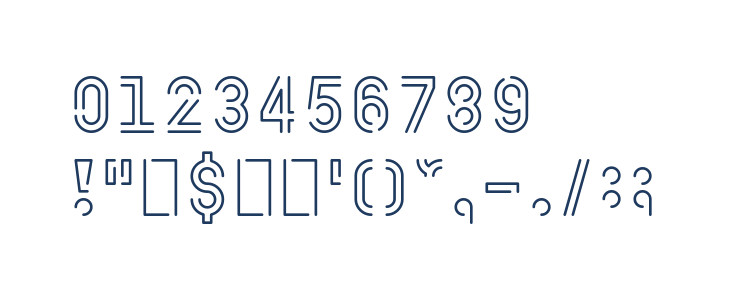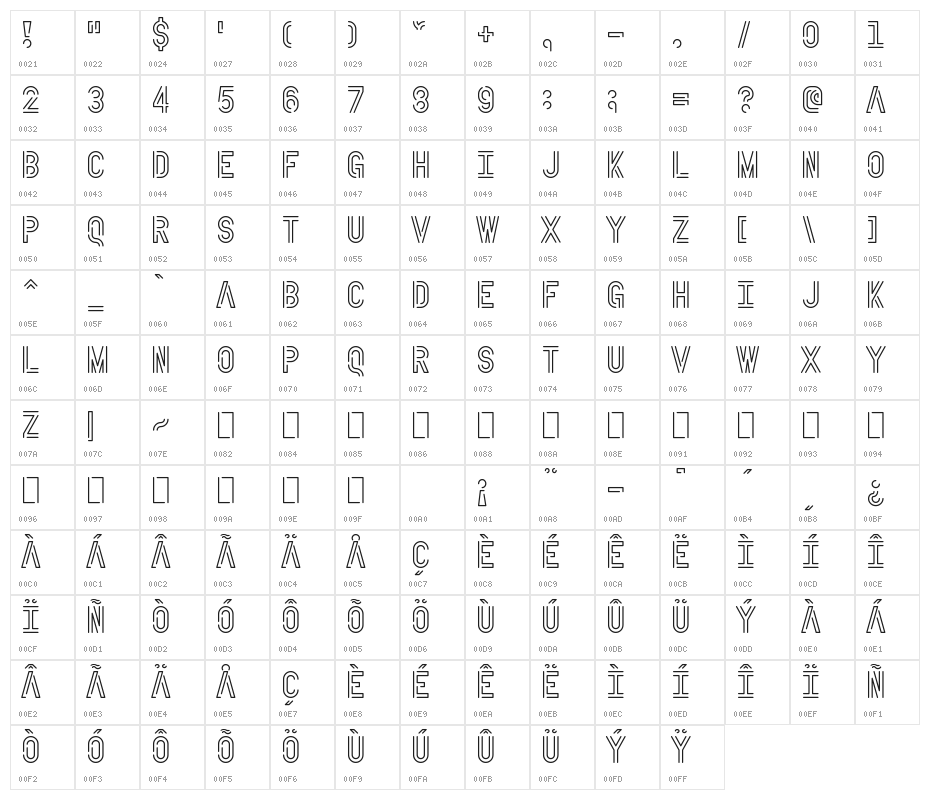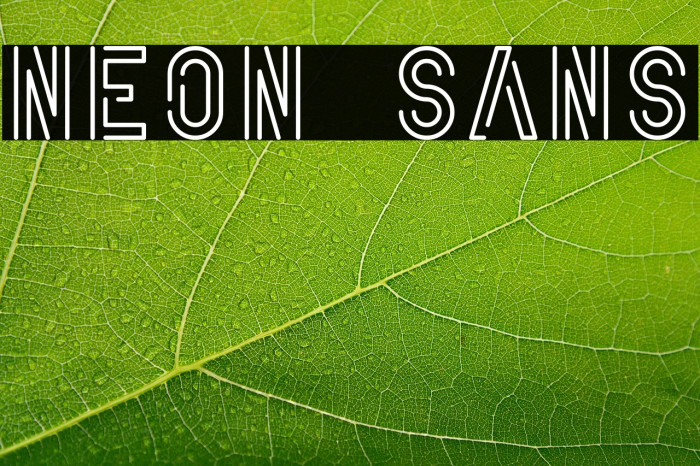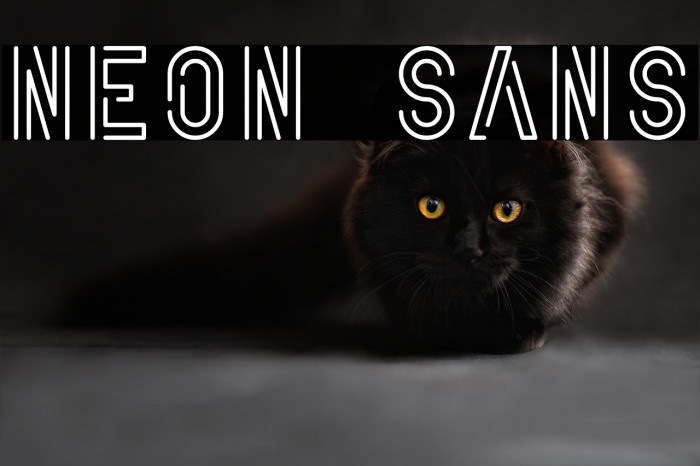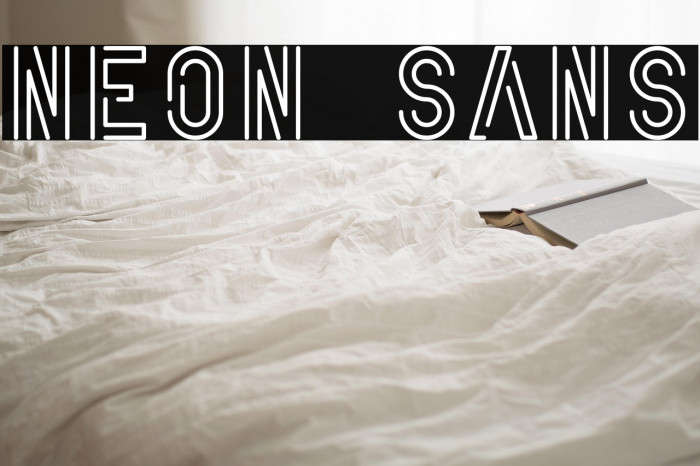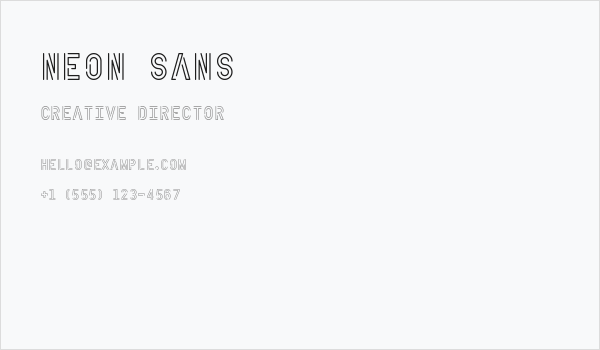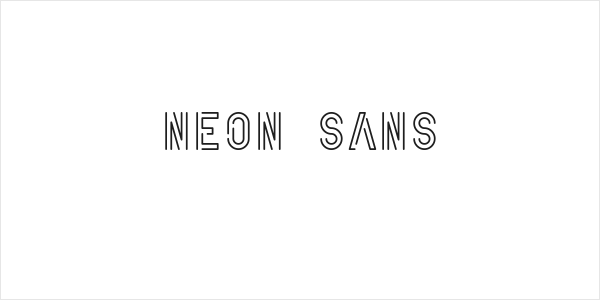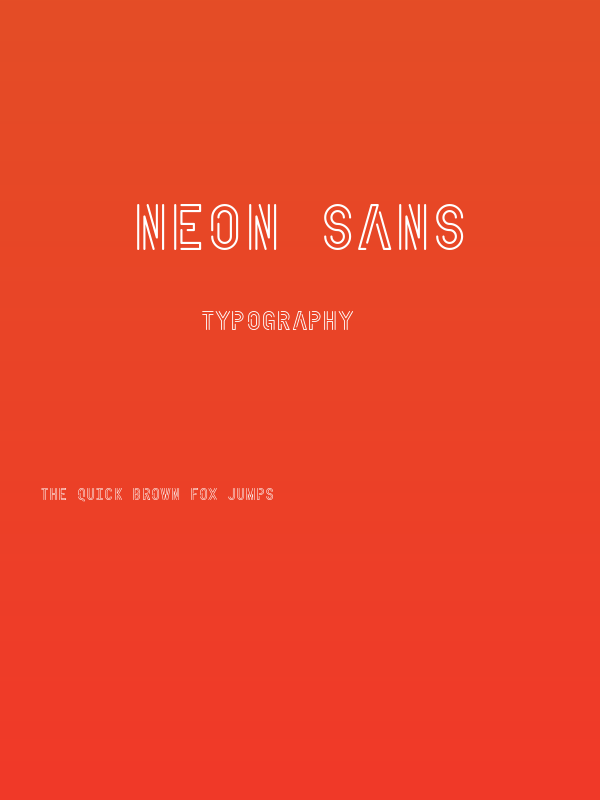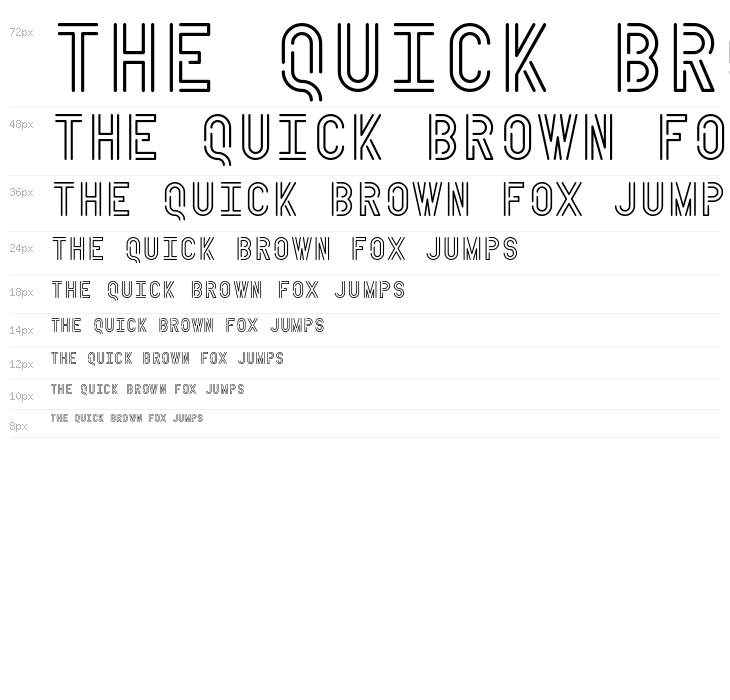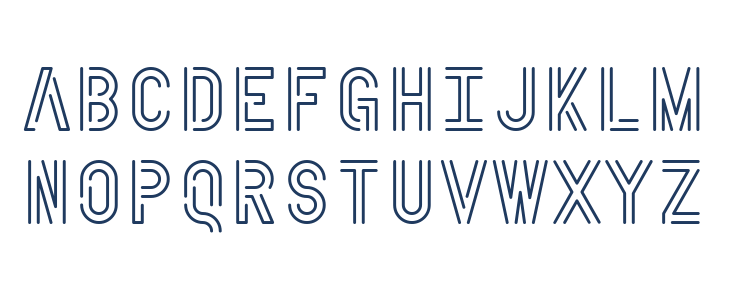
Neon Sans Font
| Vorgeschlagene Projekte | Ideal for projects requiring a futuristic or industrial aesthetic, such as tech branding, event posters, or digital media. |
Neon Sans